Elegir una fuente puede crear o romper una identidad de marca. Una gran fuente puede hacer que un transeúnte se detenga en seco o deje de desplazarse en las redes sociales. Las fuentes transmiten personalidad, significado, historia y carácter. Básicamente, las fuentes dan vida a una marca.
Pero con los millones de fuentes disponibles en Internet, es difícil decidir cuáles usar al construir su marca.
Si bien es fácil sentirse abrumado, la verdad es que la mayoría de las fuentes son solo variaciones de los cuatro tipos de fuentes principales. Si comienza por comprender la diferencia entre estas cuatro categorías de fuentes, le será mucho más fácil hacer su elección.
Repasemos los cuatro tipos principales de fuentes, lo que dicen sobre tu marca y veamos algunos ejemplos específicos.
Tipos de fuentes
- Alguacil
- Sans serif
- Guión
- Decorativo
1. alguacil
Las fuentes Serif fueron las primeras fuentes utilizadas masivamente en la impresión. Tener una cita volver a 1400Las fuentes serif tienen trazos decorativos en los extremos de cada trazo que imitan un bolígrafo o una pluma.
Diseñado por William Caslon en 1734, Old Style fue quizás la primera fuente serif en llegar al mercado. Didot y Bodini siguieron su ejemplo poco después y siguen siendo opciones serif populares para las marcas en la actualidad.
¿Qué dicen las fuentes serif sobre la marca?
Dada su historia, estas fuentes dan a la marca un sentido de atemporalidad y tradición. Marcas como Rolex, Mercedes, Prada y Dior usan fuentes serif en sus logotipos.
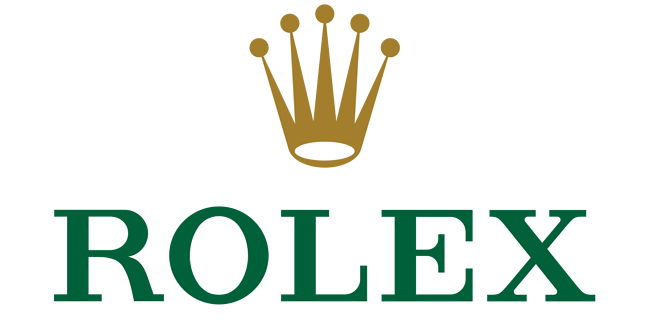
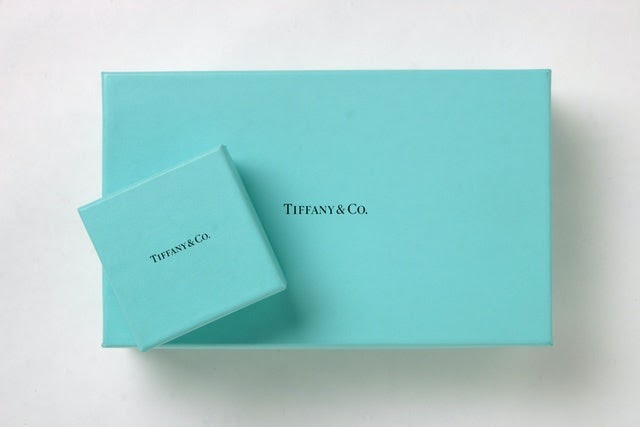
Ejemplos de fuentes serif
Hay miles de fuentes serif, pero algunas de las más populares son:
- Bodini
- Garamond
- Fuente Times New Roman
Aspectos a tener en cuenta al utilizar tipografía serif
Al elegir una fuente para su marca, debe tener en cuenta la percepción que está tratando de crear entre su público objetivo. Si espera recordar su sentido de la clase del viejo mundo, la fuente serif es la elección correcta.
¿Qué empresas deberían usar fuentes serif?
Las fuentes Serif son una opción elegante para todas las empresas, pero aquellas que tienen décadas de práctica se beneficiarán de las fuentes Serif. Aquí hay algunas categorías comerciales que a menudo usan fuentes serif en su marca:
- Periodismo
- hacer joyas
- Ley
- Finanzas
- producción de muebles
- Servicios de bienestar
2. Sans serif
Sans serif es una alternativa nítida y moderna al tipo de letra serif.
Sans serif son conocidos por su claridad y legibilidad. Úsalos cuando quieras compartir información de manera fácil, clara y directa. Se pueden usar en los más ligeros para una apariencia aireada o en los más pesados para una apariencia más atrevida.
¿Qué dicen las sans serifs sobre la marca?
Aunque el primer sans serif se diseñó en 1816, estos tipos de letra suelen ser utilizados por empresas que buscan un aspecto futurista, como las empresas de tecnología. Empresas como Google, Facebook y Netflix utilizan sans serif en sus logotipos.
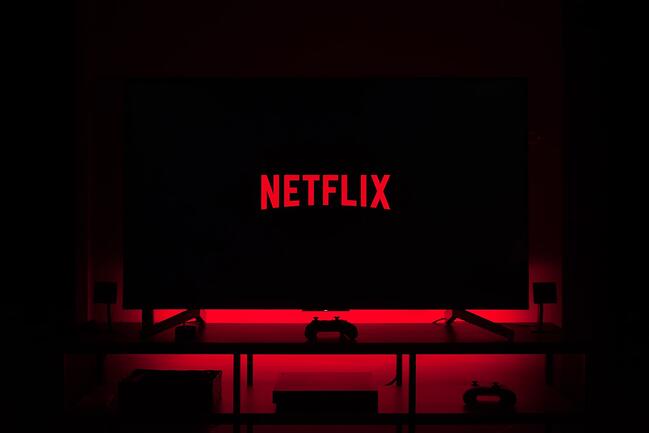
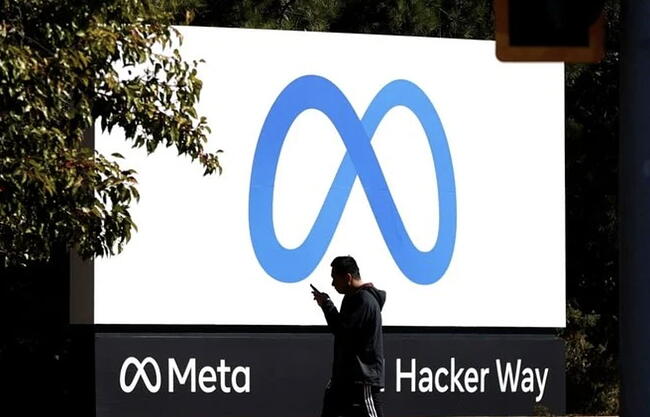
Ejemplos de fuentes sans-serif
Sans serifs son conocidos por sus líneas nítidas. Algunas fuentes serif populares incluyen:
- Helvética
- Próxima Nova
- futura
- abrir sans
Cosas a considerar al usar el tipo de letra Sans Serif
Una excelente manera de ganar interés visual al usar fuentes sans-serif es mezclar diferentes pesos de la misma familia de fuentes. Esto mantiene su marca pulida mientras agrega una sensación de profundidad.
¿Qué empresas deberían usar fuentes sans-serif?
Las fuentes Sans-serif son una excelente opción para las empresas que buscan un aspecto limpio y moderno. Su versatilidad es adecuada para muchas categorías comerciales diferentes, tales como:
- Tecnología
- Juego
- Consultante
- Moda
- Coches
- Producción
3. Guión
La escritura a mano o cursiva tiene elementos curvos y delicados que imitan la escritura a mano.
Estas fuentes generalmente se dividen en opciones más formales o informales. A menudo te encuentras con fuentes de escritura formales que se usan en eventos nocturnos, mientras que las fuentes de escritura normales se pueden usar para vestir casi cualquier tipo de marca.
¿Qué dicen las fuentes de escritura sobre la marca?
Mientras que algunas fuentes de escritura pueden ser muy decorativas y más femeninas, otras pueden parecer más informales y retro. Marcas como Ray Ban, Kellog’s, Sharpie y Kleenex utilizan fuentes cursivas en sus logotipos.
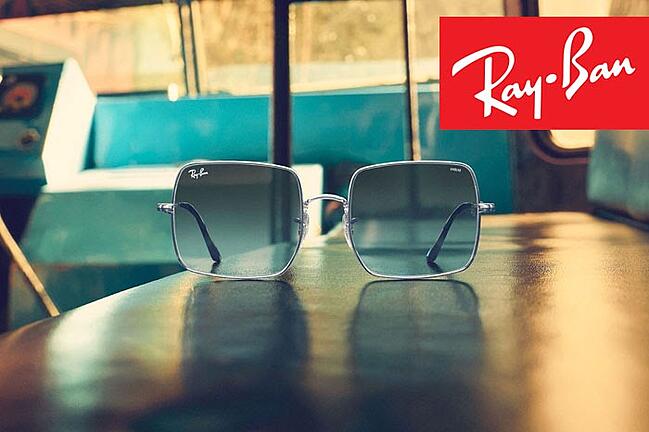
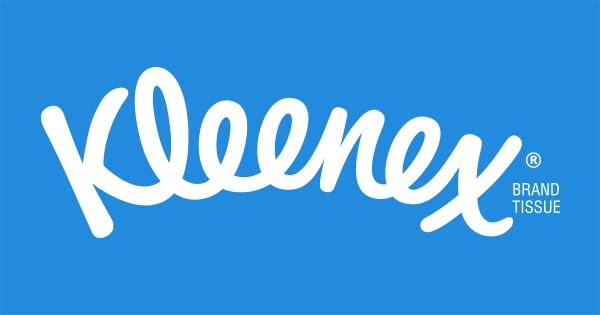
Ejemplos de fuentes de script
Las fuentes en cursiva van desde estilos caligráficos hasta estilos manuscritos más expresivos. Algunas opciones populares son:
- Pacífico
- París
- Allura
- Langosta
Aspectos a tener en cuenta al utilizar una tipografía
El uso de una fuente de escritura para su marca es una excelente manera de agregar una sensación lujosa o retro a la identidad de su marca. Como son muy decorativas, pueden resultar difíciles de leer, por lo que te recomendamos que las utilices únicamente para palabras y frases cortas.
Las fuentes de script suelen ser más adecuadas para tamaños más grandes. Cuanto más pequeños son, menos legibles se vuelven.
¿Qué empresas deberían usar fuentes script?
El uso de una fuente de script agrega un sentido de clase y elegancia a la personalidad de su marca, lo que la convierte en una buena opción para las siguientes categorías comerciales:
- Hospitalidad
- Belleza
- Salud y buen estado
- tatuaje y piercing
- Marcas retro (por ejemplo, salones de peluquería)
4. Decorativo
Las fuentes decorativas o de exhibición tienen personalidad. Estas fuentes son versiones ricamente elaboradas de sans-serif, serif, script y otras fuentes. El propósito de usar una fuente decorativa es llamar la atención con un aspecto verdaderamente único. Las fuentes decorativas vienen en muchas variedades y, a menudo, se usan en logotipos, vallas publicitarias, carteles, portadas de libros y titulares para diferenciar su marca.
¿Qué dicen las fuentes decorativas sobre la marca?
Dada la variedad de opciones de fuentes decorativas, el impacto de su marca varía. Las fuentes decorativas pueden inspirarse en muchas estéticas, ya sea una fuente de plantilla antigua, una fuente de caligrafía elegante o una placa serif masiva.
Lo mejor cuando se trabaja con una fuente decorativa es seleccionar el efecto que desea crear y luego elegir una fuente de este. Si elige algo elegante, es poco probable que elija una fuente decorativa gruesa de alta tecnología.
Marcas como Sega, Baskin Robbins y Tesla utilizan fuentes decorativas en sus logotipos y materiales de marca.
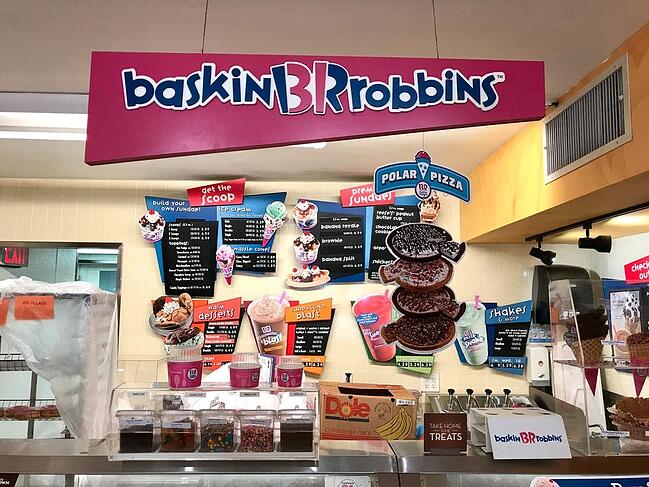
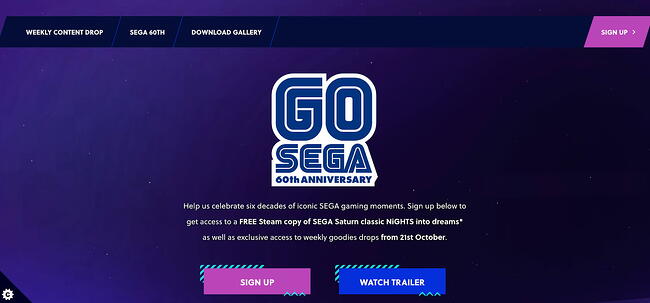
Ejemplos de fuentes decorativas
- Cobre Negro
- fuente bourton
- abril cara gorda
- Gilroy
- Gazpacho
Aspectos a tener en cuenta al utilizar una tipografía decorativa
Las fuentes decorativas ofrecen una apariencia de marca personalizada y están reservadas para formatos grandes e independientes. Úsalos cuando diseño de logo, en titulares o frases impresas (por ejemplo, en una camiseta). Evite el uso de fuentes sofisticadas en el cuerpo del texto, ya que a menudo se pierden detalles.
¿Qué empresas deberían usar fuentes elegantes?
Las fuentes decorativas realmente se pueden usar en cualquier tipo de negocio. A menudo los vemos en empresas creativas como:
- Juego
- dulce
- Alimentos y bebidas
- Automotor
- Artículos para el hogar
- Artículos para niños y bebés
Selección de tipo de fuente
Las fuentes son una parte poderosa del diseño de marca. Transmiten energía, emociones y personalidad. Si bien hay miles de fuentes diferentes para elegir en Internet, es más fácil de entender y pasar de los cuatro tipos principales de fuentes.
Antes de hacer su selección final, considere lo que dice su selección de fuente sobre su marca. Recuerda:
- Las fuentes Serif le dan a la marca un aspecto atemporal y tradicional.
- Las fuentes sans-serif enfatizan el carácter moderno de la marca.
- Las fuentes Script le dan a la marca un sentido de elegancia.
- Las fuentes decorativas están llenas de personalidad y transmiten un aspecto personalizado.